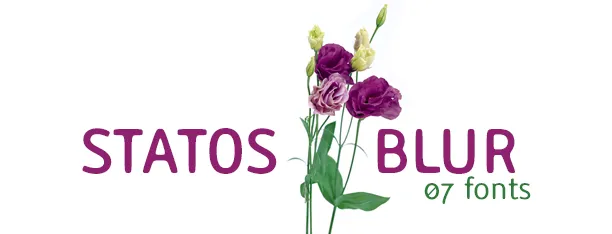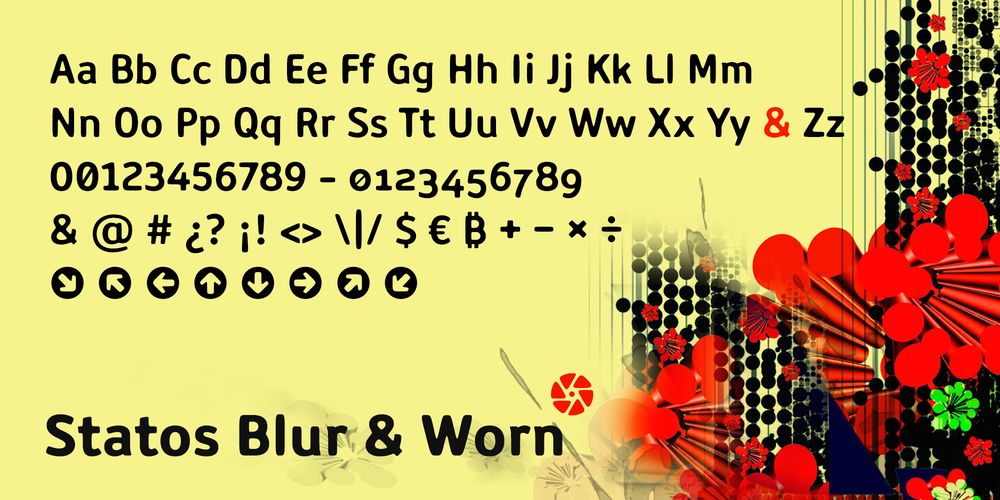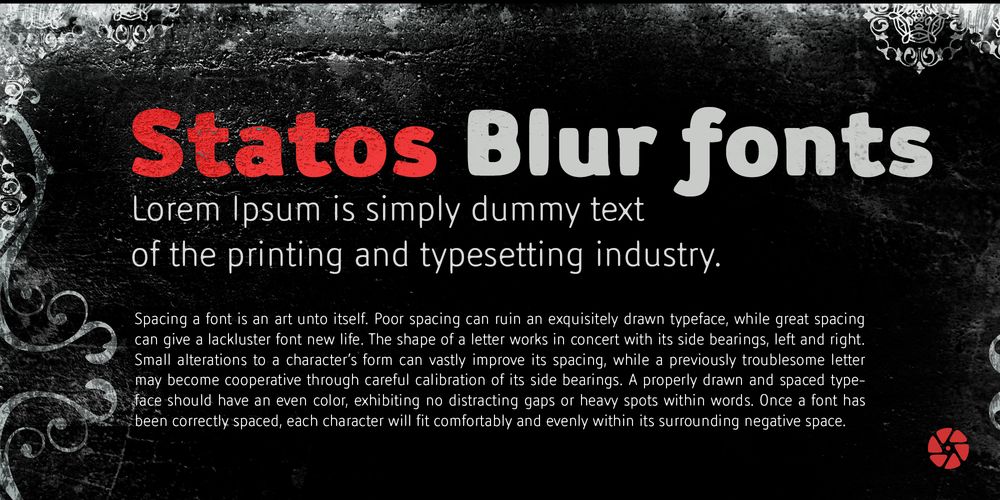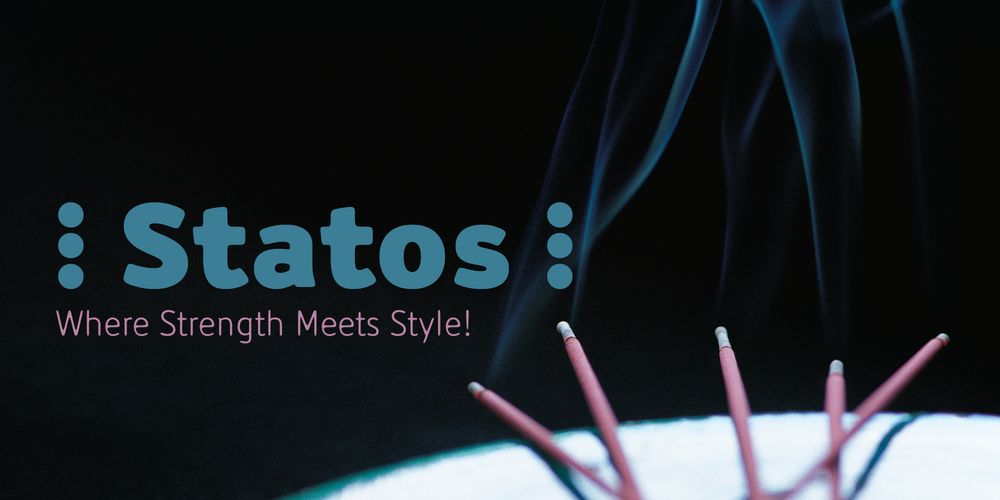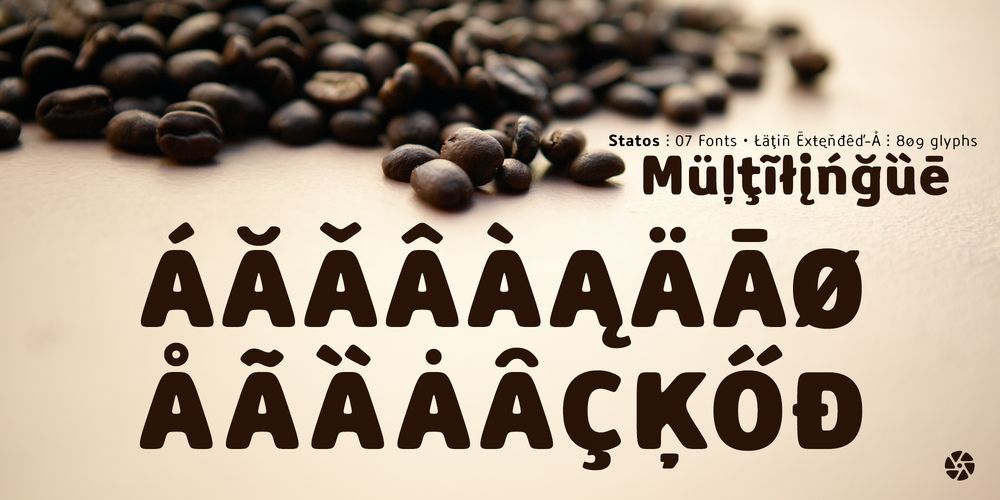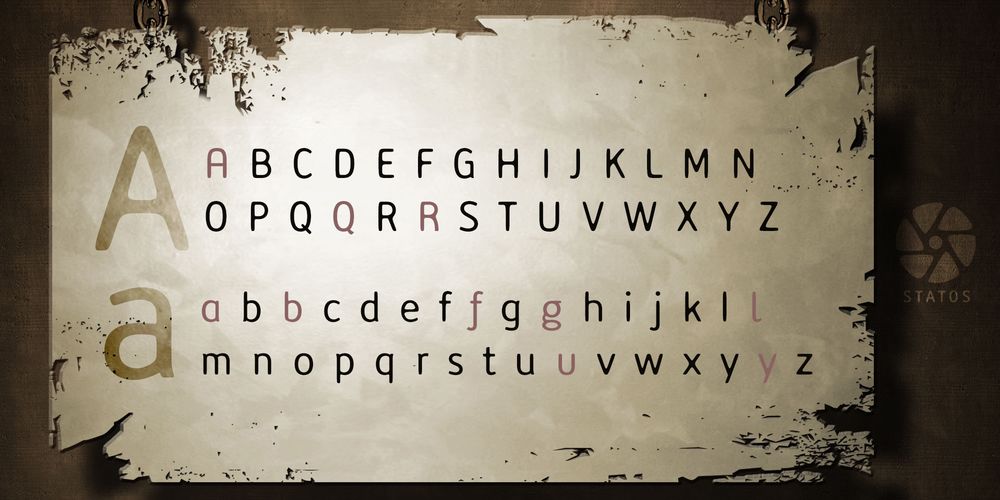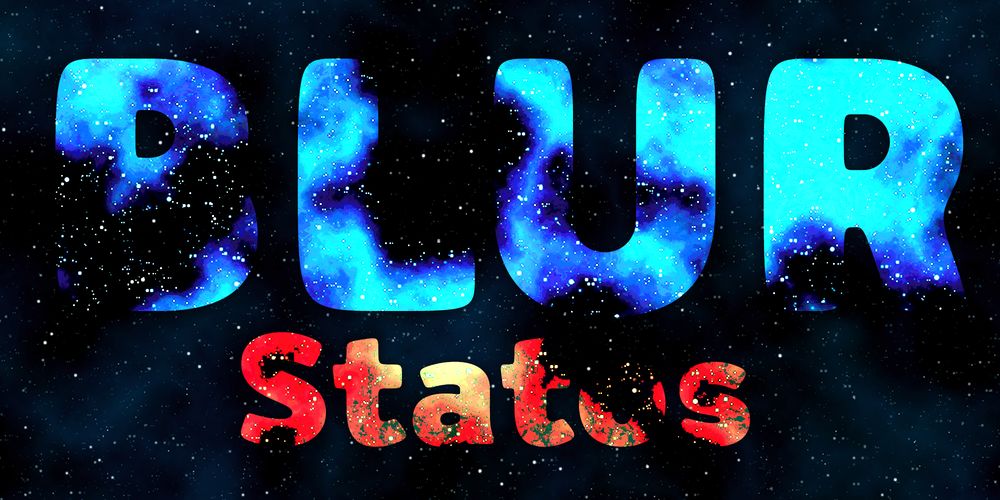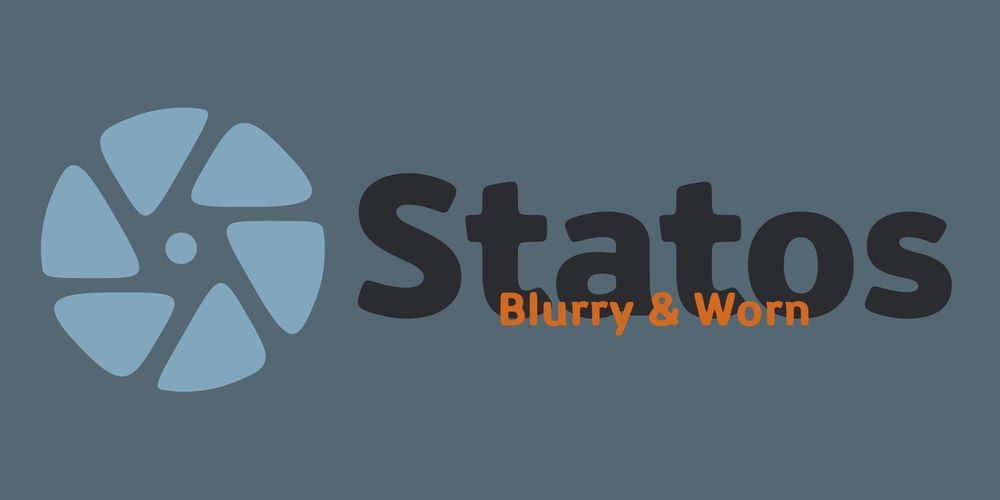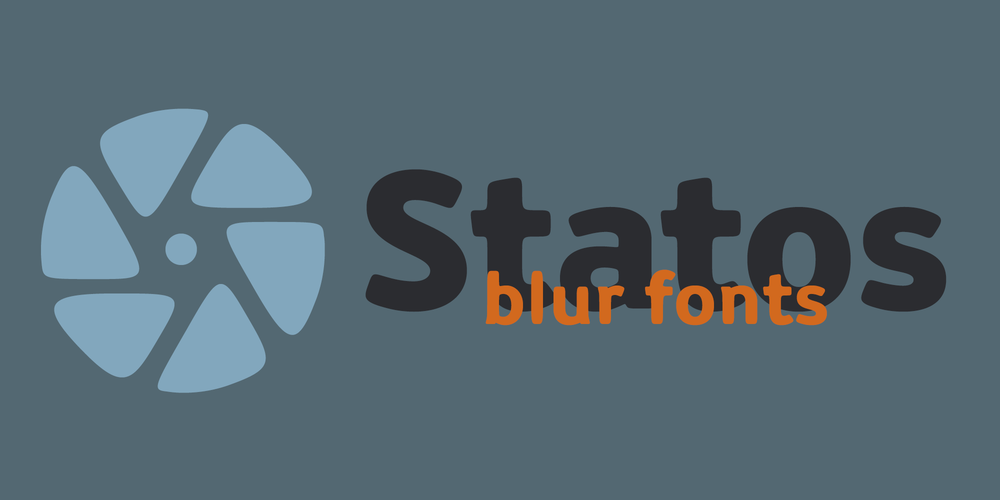
Blurred & Worn Typefaces
Estilo: Worn, Blur, Distressed, Sans Serif, Display, Editorial, Branding
Proporción: Light, Regular, Medium, Semi Bold, Bold, Extra Bold, Black
Glyphs: 809
Alternates: 242
Latin-Extended: Latín Básico, Europa Occidental, Central & Oriental.
809 glyphs w/ 241 alternates: Numbers, Signs & Letters
Statos cuestiona la perfección tipográfica. Se aleja de la limpieza absoluta para abrazar lo imperfecto como lenguaje visual. Y sin embargo mantiene una legibilidad excepcional. Lo deteriorado no sacrifica lo legible. Eso es el equilibrio que persigo. Statos abraza la imperfección.
Inspirada en la gráfica industrial recuperada, la señalética urbana erosionada por el tiempo y las impresiones sometidas al roce constante del mundo real; cada letra y número en Statos lleva la marca del paso del tiempo, una crudeza controlada que transmite autenticidad y fuerza. Statos es un tributo visual a la resistencia, hay una tensión constante entre lo funcional y lo deteriorado. Cada borde suave, cada desenfoque controlado, cada imperfección está diseñada para no romper la lectura, sino para darle carácter.
La familia se estructura en 07 pesos, siete estados de decadencia controlada —Light, Regular, Medium, Semi Bold, Bold, Extra Bold y Black— que mantienen esa identidad erosionada sin sacrificar jerarquía ni rendimiento. No importa si estás diseñando un titular contundente o un bloque editorial: la voz se mantiene coherente, firme, reconocible.
Statos lleva consigo seis juegos completos de números para que cada cifra cuente su propia historia. Tres juegos de mayúsculas que dialogan entre sí. Cinco juegos de minúsculas porque la versatilidad no negocia con la monotonía.
Dos juegos de flechas para señalar direcciones en este caos visual que llamamos diseño; y 242 caracteres y signos alternativos que amplían el lenguaje visual mucho más allá de lo básico. Porque el diseño no se hace con lo mínimo indispensable, se hace con herramientas que te permiten decidir en el momento de la verdad.
🧲 Las funciones OpenType están pensadas para diseñadores que quieren control real:
- Números y letras posicionales (ordinales, denominadores, numeradores, inferiores científicos) para construir fracciones y fórmulas con precisión
- Signos de puntuación decorativos que convierten la microtipografía en un recurso expresivo: tricolons, referencemarks, dottedcrosses, five dot punctuations, vertical four dots, asterismos, therefore, because…
- Alternate Annotation Forms: Acceso a glifos de números y letras mayúsculas encerrados en círculos sólidos (blackcircle) y delineados (circlewhite), donde los caracteres se convierten en señalética.
- Ligaduras Estándar y Discrecionales: Para dar fluidez y un toque editorial único a los títulos.
- Además, incorpora flechas que apuntan a lo esencial, símbolos monetarios internacionales y las principales Criptomonedas (Bitcoin, Ethereum, etc.), porque el lenguaje contemporáneo también pasa por ahí.
Statos habla donde haga falta. Sin complejos, sin barreras. Latin Extended-A: El Idioma de lo Universal.
🎯 ¿Dónde Funciona Statos?
Statos se adapta con facilidad a proyectos comerciales que requieran autenticidad, vibra urbana, o un toque humano y artesanal. La he diseñado principalmente para proyectos que necesitan presencia.
- Diseño Editorial y Cartelería: Aporta textura y profundidad visual a posters, fanzines, y revistas de diseño.
- Folletos que no quieren ser olvidados en la primera papelera
- Identidad de Marca y Logotipos: Para marcas con herencia, carácter urbano o perfiles ecológicos/artesanales.
- Packaging de Producto: Ideal para etiquetas de cerveza artesanal, café, ropa urbana o productos orgánicos.
- Señalización y Arquitectura Efímera: Legible a gran escala, ideal para espacios comerciales modernos y rústicos.
Añade peso, historia y textura a tu caja de herramientas de diseño. Statos es un abrazo a lo imperfecto como lenguaje visual, no es una tipografía limpia, sino una tipografía honesta. No es una forma perfecta, sino una forma que ha resistido. Y en esa resistencia, encuentra su verdadero estilo.